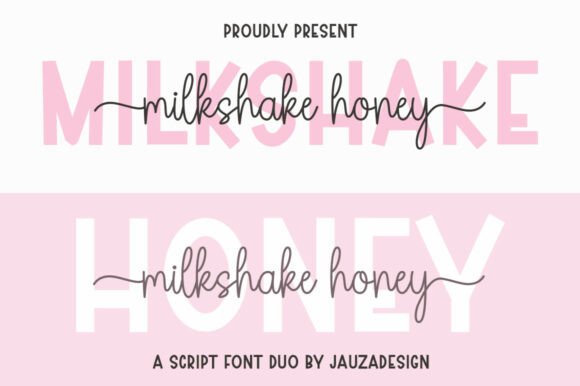
Milkshakehoney
Jika anda sedang mencari aset berkualiti tinggi seperti Milkshakehoney, pakej premium ini merupakan pilihan yang hebat untuk projek kreatif anda.
Dicipta dengan ketepatan, Milkshakehoney menyediakan vektor yang bersih, tipografi yang licin dan lesen komersial untuk ketenangan fikiran.
Sama ada anda mencipta produk POD (Print on Demand), jemputan perkahwinan atau grafik media sosial, Milkshakehoney amat bersesuaian.